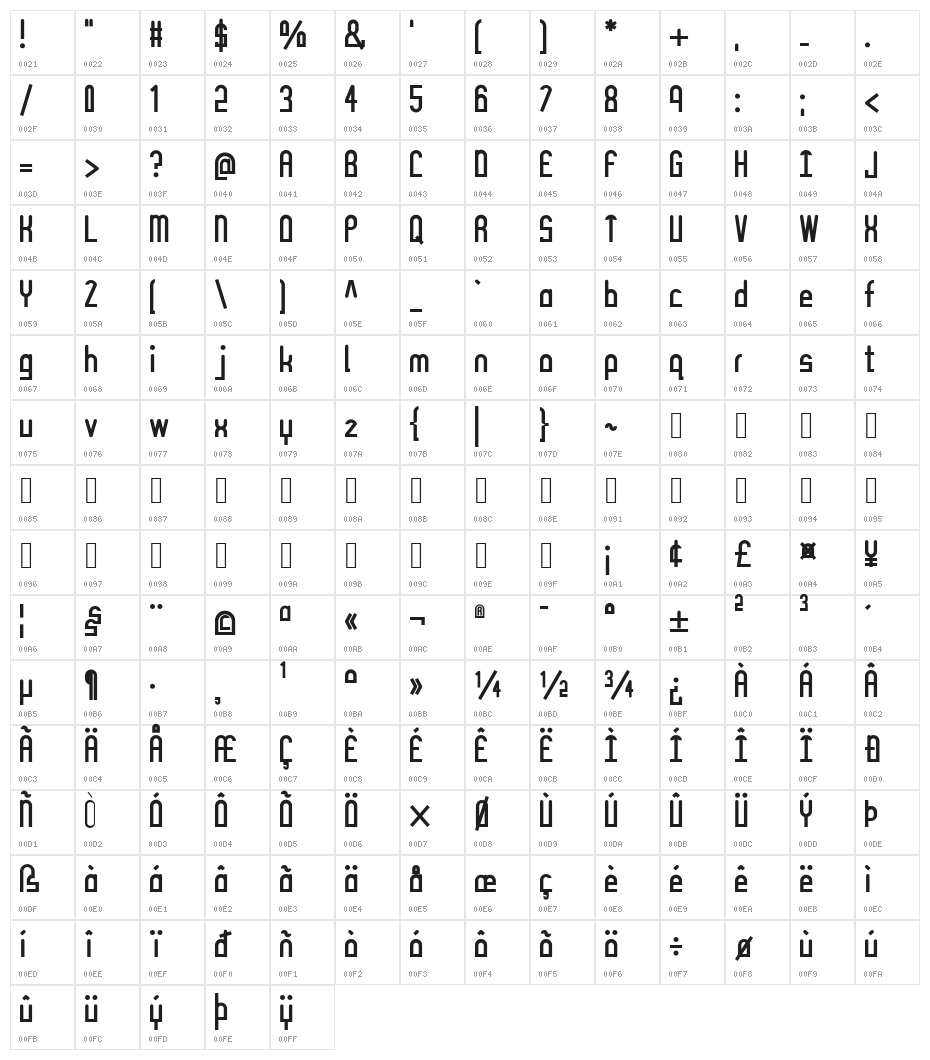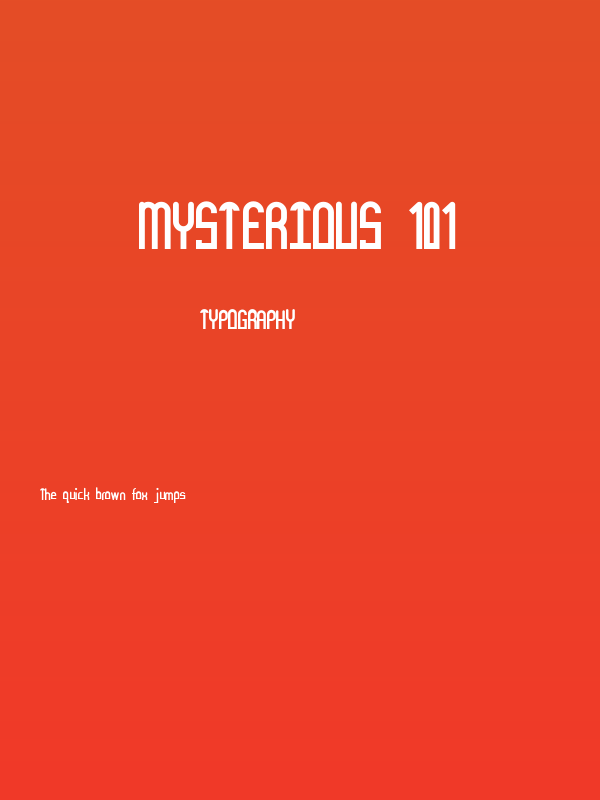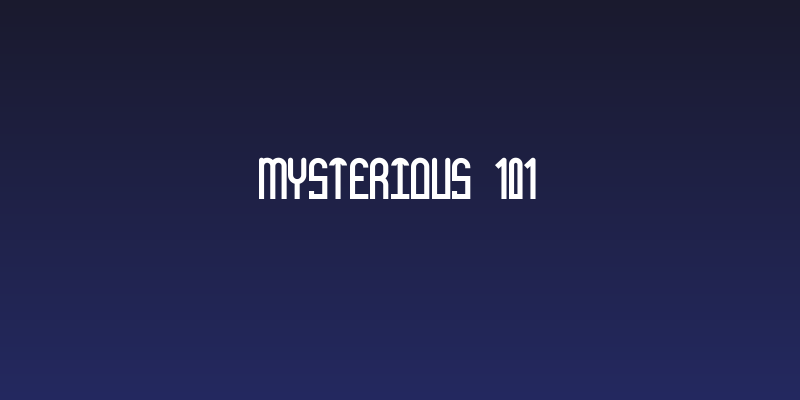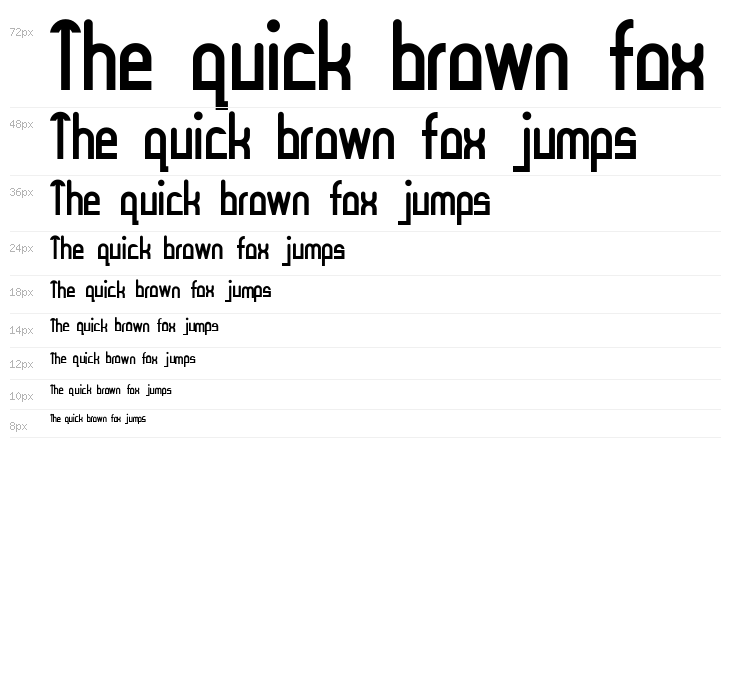
Mysterious 101 Font
| Progetti proposti | Ideal for branding, posters, headlines, and digital media projects that require a modern and bold aesthetic. |